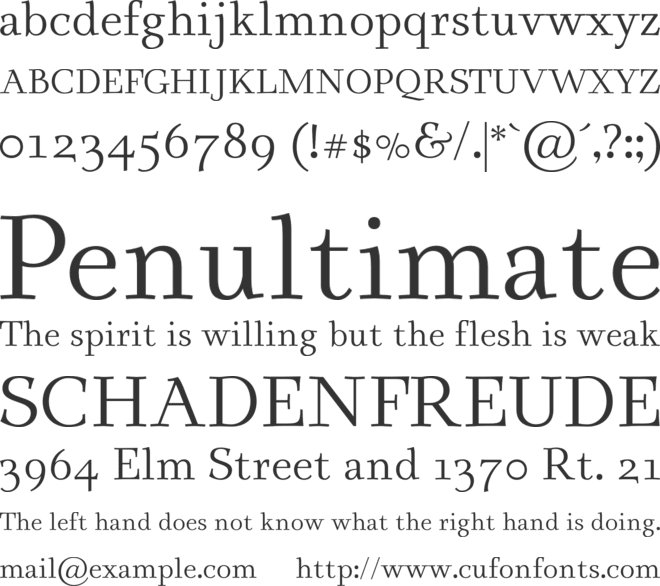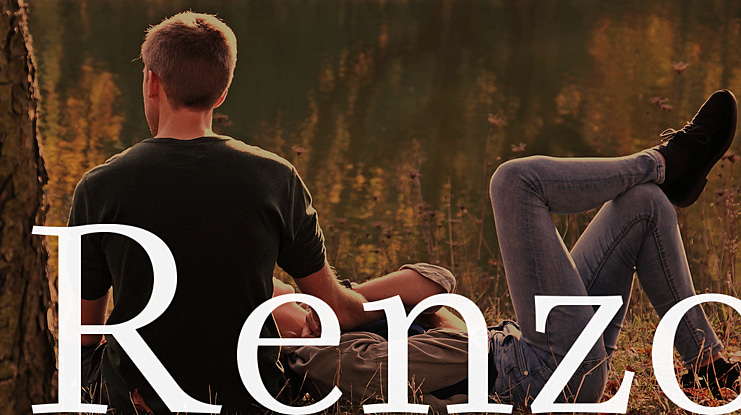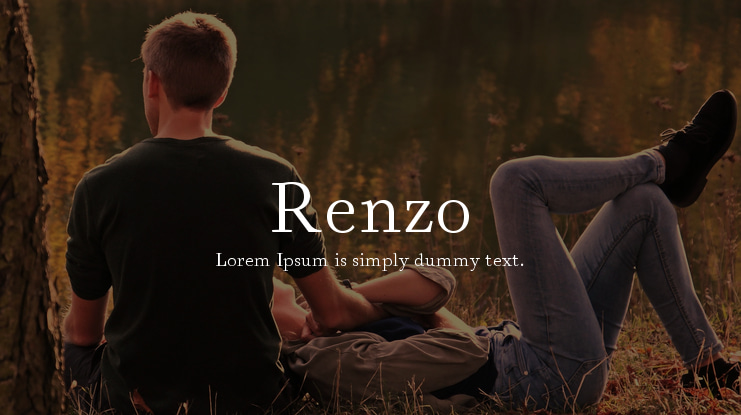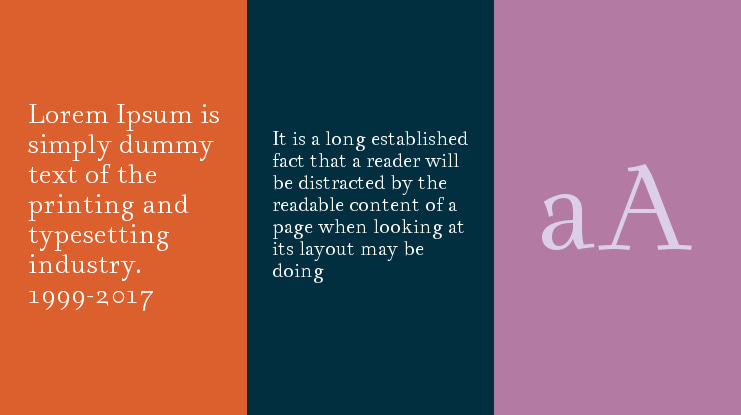
Renzo Font
Renzo, es una tipografía para texto continuo, creada para ser utilizada principalmente, en documentos que contemplen párrafos de corta extensión, como revistas, boletines, comunicados y notas.
Renzo se presenta imponente en el papel, permitiendo una atractiva experiencia de lectura y excelente legibilidad.